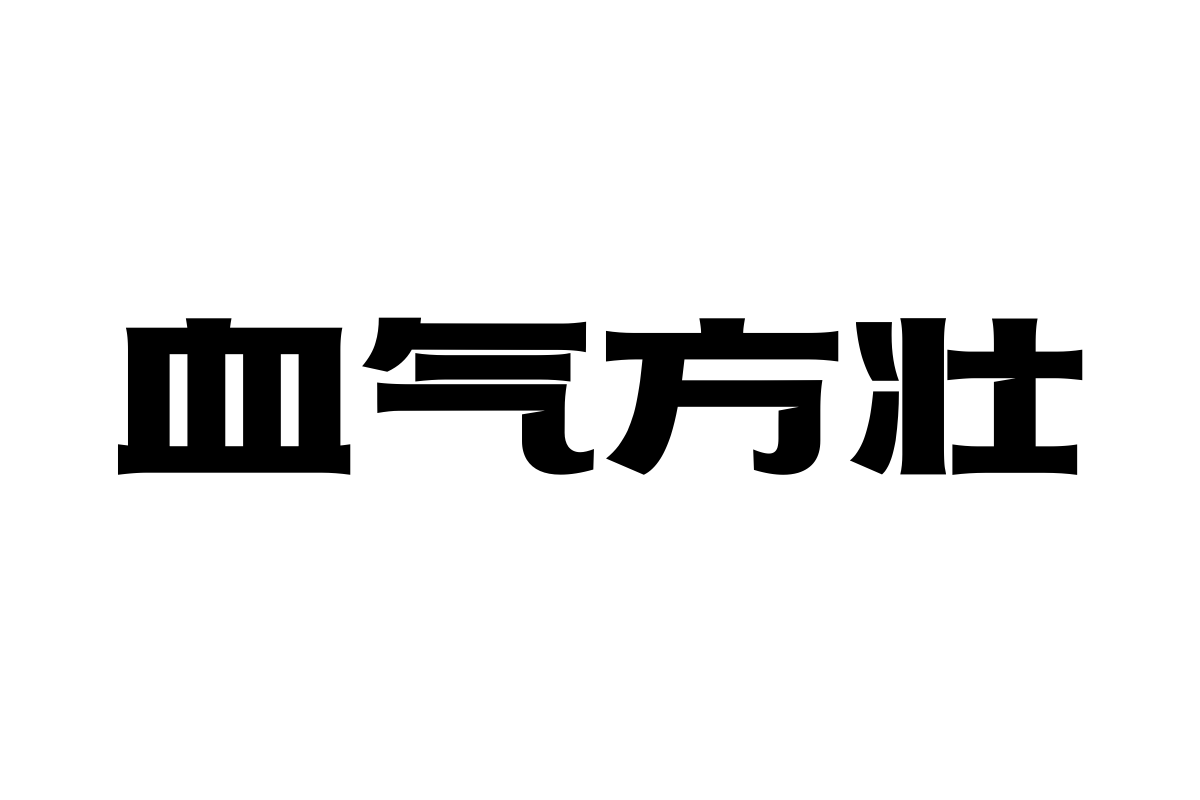
上首几何体是一种字体,它的特点是笔画粗细变化明显,具有独特的美感。这种字体适合用于标题、广告、海报等需要突出视觉效果的场合。
上首几何体的特点如下:
1. 笔画粗细变化明显:上首几何体的笔画粗细变化较大,使得字体看起来更加醒目和有冲击力。
2. 独特的美感:上首几何体的线条流畅,形状各异,给人一种独特的美感。
3. 适用于多种场合:上首几何体适用于标题、广告、海报等多种场合,能够有效地吸引人们的注意力。
4. 易于识别:由于笔画粗细变化明显,上首几何体具有较高的可读性,便于人们快速识别和理解。
总之,上首几何体是一款具有独特美感和实用性的字体,适合用于需要突出视觉效果的场合。